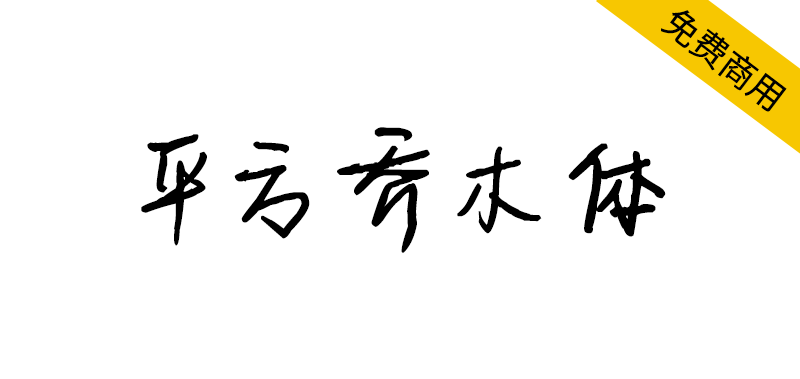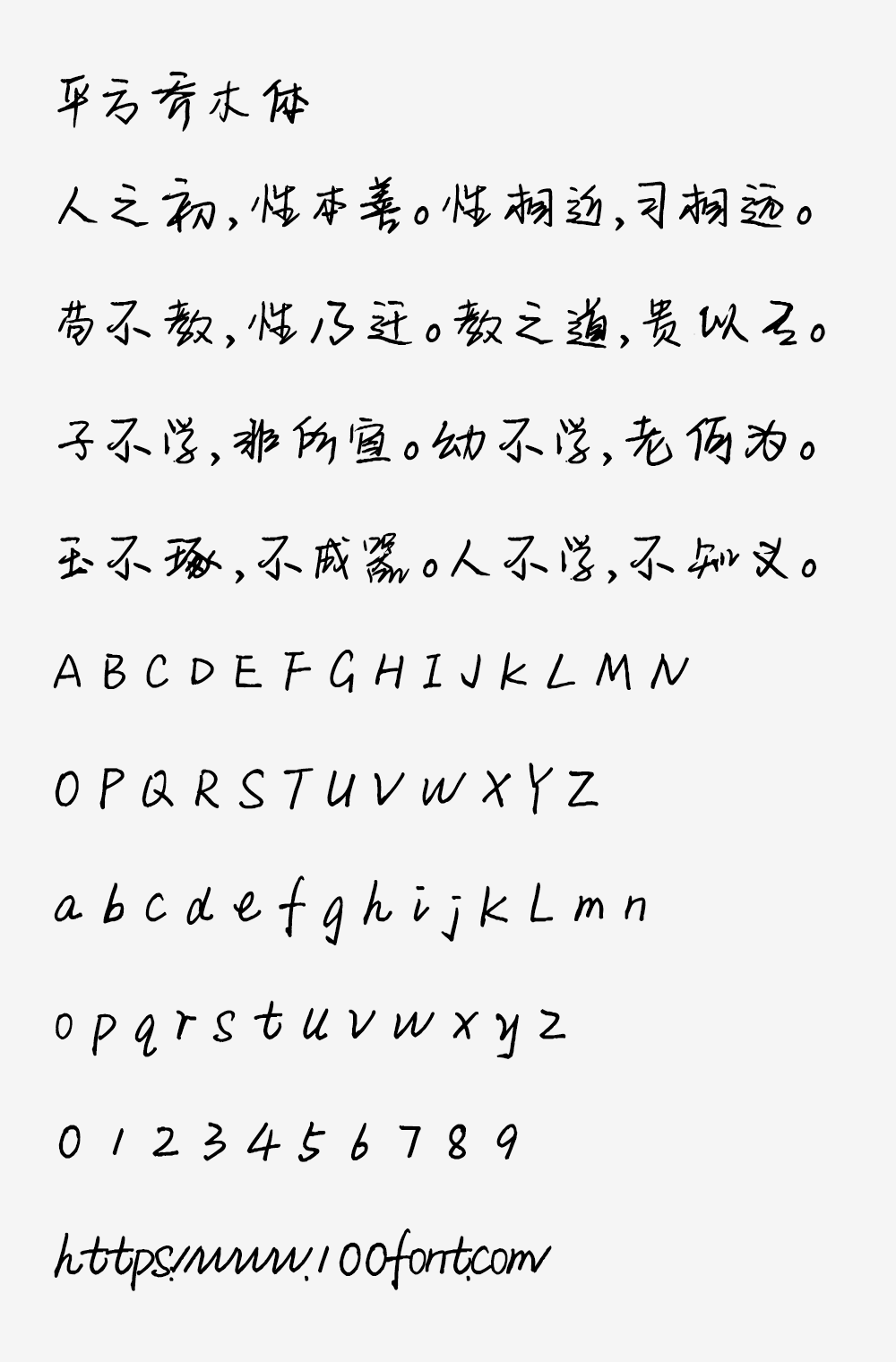
【平方乔木体】一款笔画纤细的创意手写体字体
还在为设计作品缺乏个性而苦恼?这款免费可商用的手写字体将彻底改变你的创作体验!平方乔木体以其纤细流畅的笔画和自然连贯的书写感,为设计注入独特温度。无论是平面广告、自媒体配图还是电商设计,它都能瞬间提升作品质感。更惊喜的是,个人和企业均可免费使用,立即输入文字在线预览,发现专属于你的创意表达方式!
【平方乔木体】一款笔画纤细的创意手写体字体
平方乔木体是一款笔画纤细的创意手写体字体,书写连贯自然,呈现出优秀的视觉效果,该字体适用范围广泛,可应用于创意艺术设计、平面广告宣传等场景